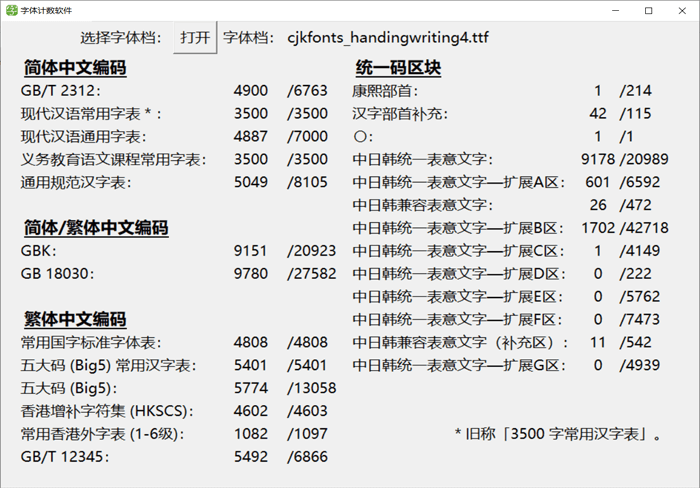
cjkFonts手写4:基于清松手写体4智能AI深度学习自动生成字体
字体作者:cjkFonts x 游清松 (中国港台) 字体字重:1个
cjkFonts手写4是基于清松手写体4透过AI深度学习造字,原本清松手写体4大约有4千几百字,使用AI已造了2万7千字,但因为要时间后期製作,现在只释出大约1万2千字,其余的字待有时间才再加入。
由于是电脑学习了字型的特点及风格后,每个字根据学习后的数据造字,所以字体的风格会跟清松手写体4有轻微的分别。
这次是1万2千字的版本,大约用了2个月时间完成制作。清松手写体4的风格跟一般字变化比较大,在整过训练过程中,要反覆检视结果,然后再训练,再检视,直至大部份的字型跟原版接近才能开始后期制作。
• 修正若干字
• 添加若干地名、人名用字
• 调整英数字距
• 支援直排
• 优化轮廓算法减少存储空间
还是缺一些字,比如“钜”
• 他介绍里面最终会完成2万多字的~
• 钜字已经有了哟
這個字形簡直就像思源黑體香港字形。因為於字右邊的第二筆是橫而不是捺。